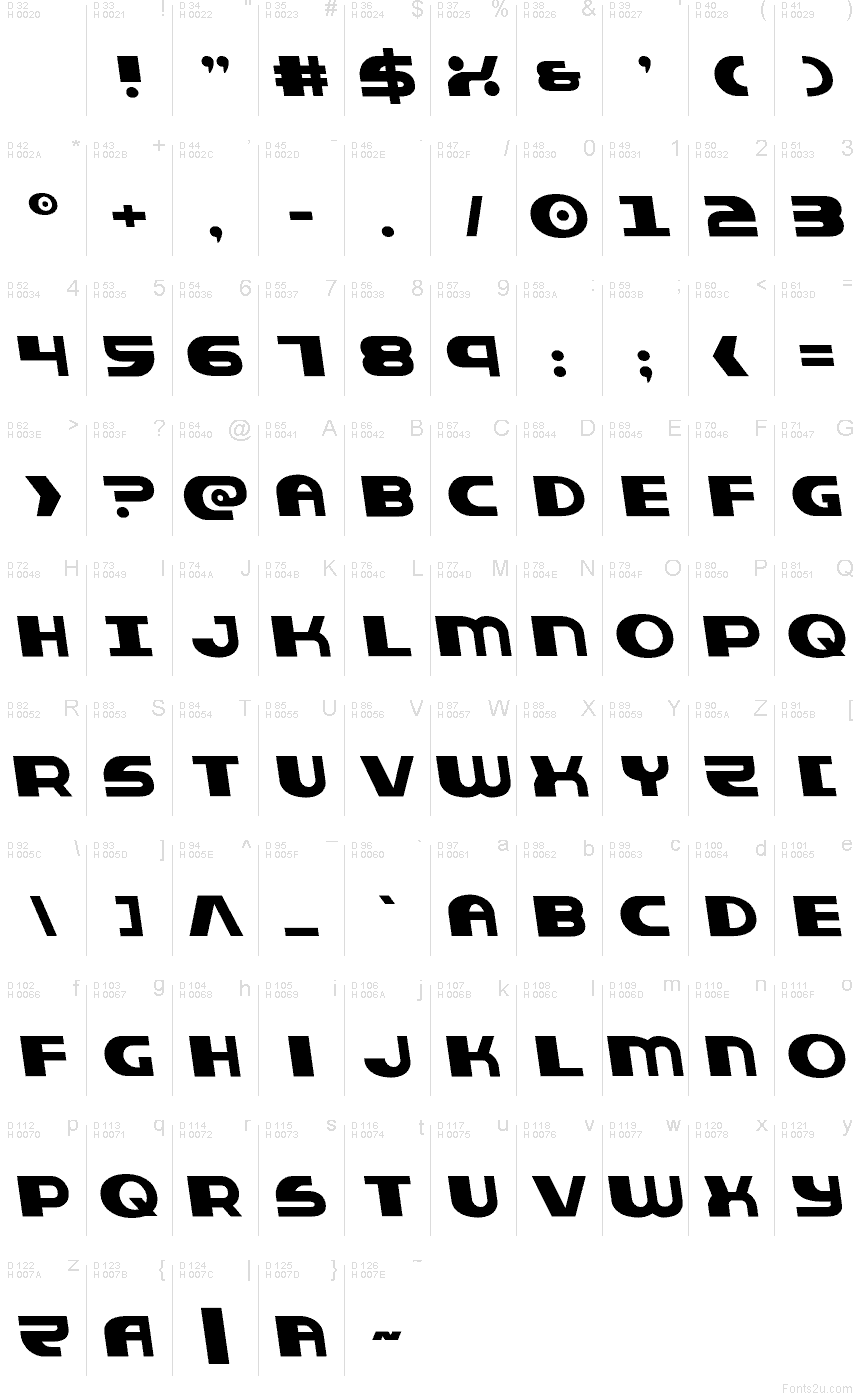
Dashiel Semi-Leftalic de Iconian Fonts es una tipografía display gratuita de ciencia ficción, creada a partir de letras mayúsculas anchas y pesadas con una distintiva inclinación hacia atrás. Las letras se sienten más construidas que ornamentadas, utilizando bordes diagonales duros y largos cortes horizontales que atraviesan los trazos curvos para lograr un ritmo tenso y dinámico.
Es ideal para logotipos de juegos, branding de esports, títulos de pósteres, packaging tecnológico y tarjetas de título donde una línea corta necesita ese toque anguloso y mecánico. Al ser una fuente gratuita, también funciona muy bien para textos de portada, monogramas y encabezados de interfaz, ya que esas formas cortadas mantienen el estilo potente incluso cuando el texto es breve.